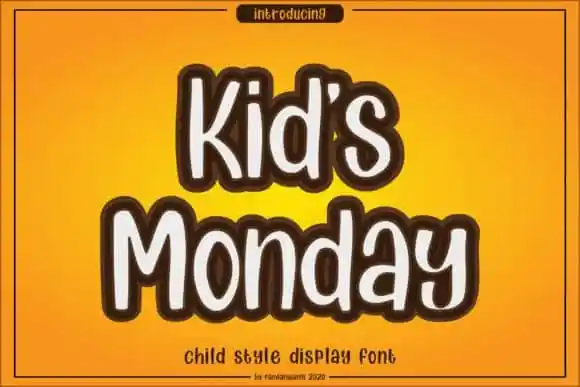
Kids Monday Display Font – Download Grátis
A Kids Monday Display Font é uma escolha perfeita para projetos criativos que desejam dar vida à sua identidade visual com um estilo único e divertido. Desenvolvida pelo designer pandanwangi, esta tipografia tem a capacidade de tornar seus designs ainda mais interessantes e memoráveis. Com seu caráter leve e encantador, essa fonte é perfeitamente adequada para trabalhos onde se deseja transmitir uma mensagem direta e entusiasmante. Com um design natural e único, Kids Monday Display Font é especialmente apropriado para aplicar em grandes projetos de piscinas. Suas características encantadoras fazem com que ela seja ótima para qualquer projeto que possa beneficiar-se daquela exuberância visual e da personalidade vibrante associada à fonte. Seja uma identidade corporativa, um slogan ou até mesmo o design de sua próxima campanha publicitária, a Kids Monday Display Font certamente deixará seu trabalho mais atrativo e memorável.